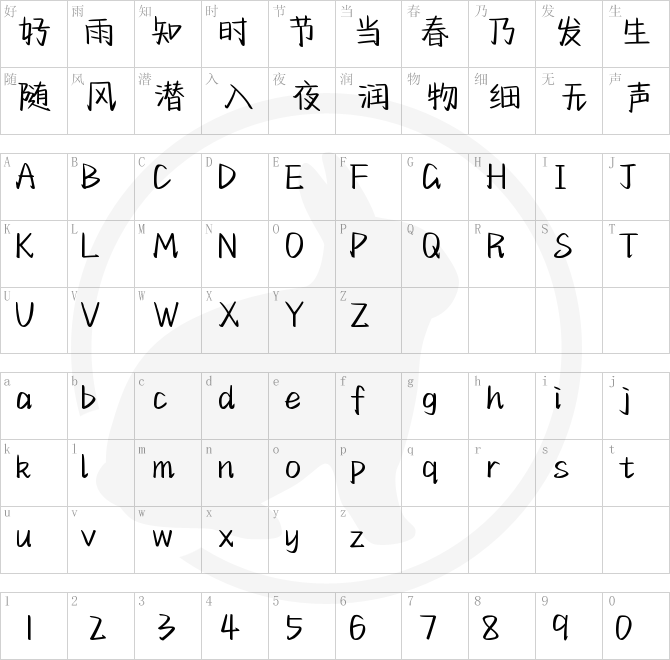
也字工厂综艺弹幕体
也字工厂综艺弹幕体,这款字体结构工整、笔画清晰,兼顾美观与易读性,适用于标题、正文、海报、包装、LOGO 等多种场景。字形优雅稳定,风格百搭耐看,适配日常排版与创意设计,让文字呈现更舒适、更具质感。也字工厂综艺弹幕体一笔一画,皆是细节,以均衡的比例、流畅的线条打造舒适视觉体验,字形端正大气,风格简约现代。无论是商业设计、品牌宣传还是日常排版,都能轻松驾驭,让文字更有格调与力量。也字工厂综艺弹幕体字体下载。